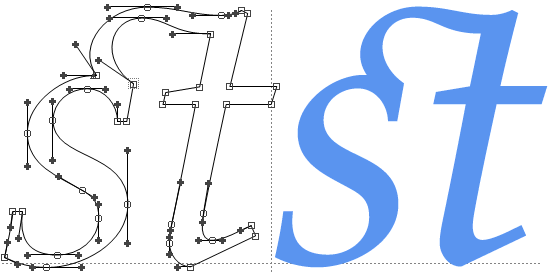
Ligatury, styl i elegancja liter
Ligatury to specjalnie zaprojektowane kombinacje liter, w których dwa lub więcej znaków łączą się w jedną estetyczną formę, dodając wyjątkowy styl i elegancję do tekstu.
Celem ligatur standardowych jest poprawa estetyki i usunięcie niepożądanych konfliktów wizualnych między literami. Dodatkowo, są one szczególnie przydatne w przypadku czcionek szeryfowych, gdzie ozdobne zakończenia liter mogą nachodzić na siebie. Wtedy używanie ligatur przekłada się na lepszą czytelność.
Z kolei ligatury ozdobne mogą być dostępne w czcionce, ale nie są domyślnie aktywowane. Są one używane bardziej selektywnie przez projektantów, aby nadać tekstowi indywidualny styl. Mogą obejmować kombinacje liter, które występują rzadziej, ale mają duże znaczenie estetyczne. Przykładem może być ligatura st występująca w zestawie Questy:
Współczesne edytory tekstu oferują wiele zaawansowanych funkcji typograficznych, w tym możliwość aktywacji i korzystania z ligatur. Pozwala to projektantom, pisarzom i edytorom na korzystanie z tych specjalnych kombinacji liter, które są dostępne w zastosowanych czcionkach.
Aby aktywować ligatury w edytorze tekstu, należy najpierw upewnić się, że używany font je posiada. Następnie można znaleźć opcję aktywacji ligatur w panelu typograficznym lub w ustawieniach czcionki. Po ich aktywowaniu, edytor automatycznie zastosuje odpowiednie ligatury na podstawie kontekstu tekstu, eliminując nieestetyczne przerwy między literami.
Zupełnie unikalne zastosowanie tych funkcji ma miejsce w naszych fontach do składu podręczników Pismo Szkolne PRO. Zastosowanie aż 650 ligatur umożliwia uzyskanie tysięcy prawidłowych typograficznie połączeń międzyliterowych szkolnego pisma dziecięcego: